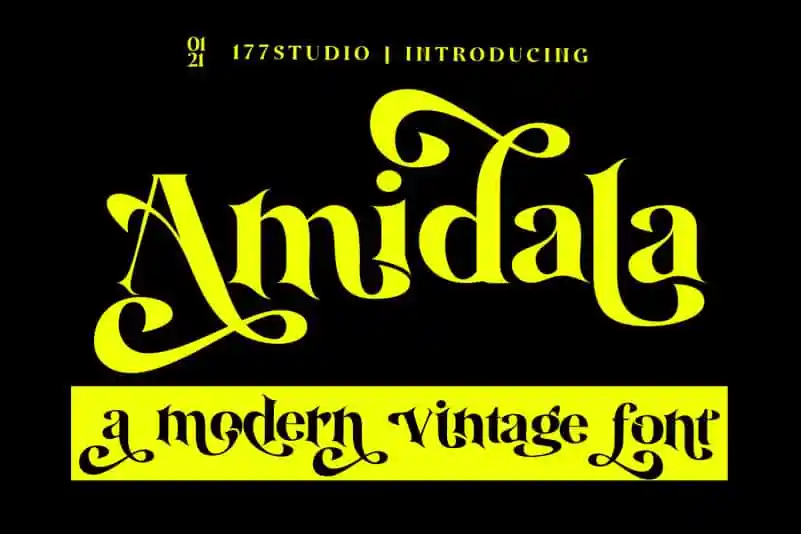
Amidala Serif Font – Download Grátis
A Amidała Font é uma fonte serif vintage estilo elegante, equilibrada para o público contemporâneo com seu desenho único e versátil. É perfeito para projetos de marca, criação de logotipos, embalagens de roupas, cabeçalhos de revistas ou até mesmo uma overlay textual sofisticada em qualquer fundo de imagem. Com suas ligações belas e inúmeras alternativas de caracteres especiais, ornamentações e suporte multilíngue, a Amidała está repleta de recursos que tornam-a uma fonte versátil. Ela é perfeita tanto para uso em grandes dimensões quanto nas aplicações menores, o que a faz ideal para aplicativos como o design de logotipos e criação de embalagens. Suas ligaturas delicadas e seu conjunto de alternativas exclusivo permitem criar texturas e gráficos impressionantes. Além disso, seu estilo minimalista elegante torna-a uma opção perfeita para branding, destacando seus elementos visuais através de uma linguagem moderna e sofisticada. Seja você um designer visual ou criativo, a Amidała Font é uma ótima adição à sua coleção. Suas características únicas combinadas com seu design versátil tornam-na uma escolha perfeita para qualquer projeto que exija estilo e qualidade.